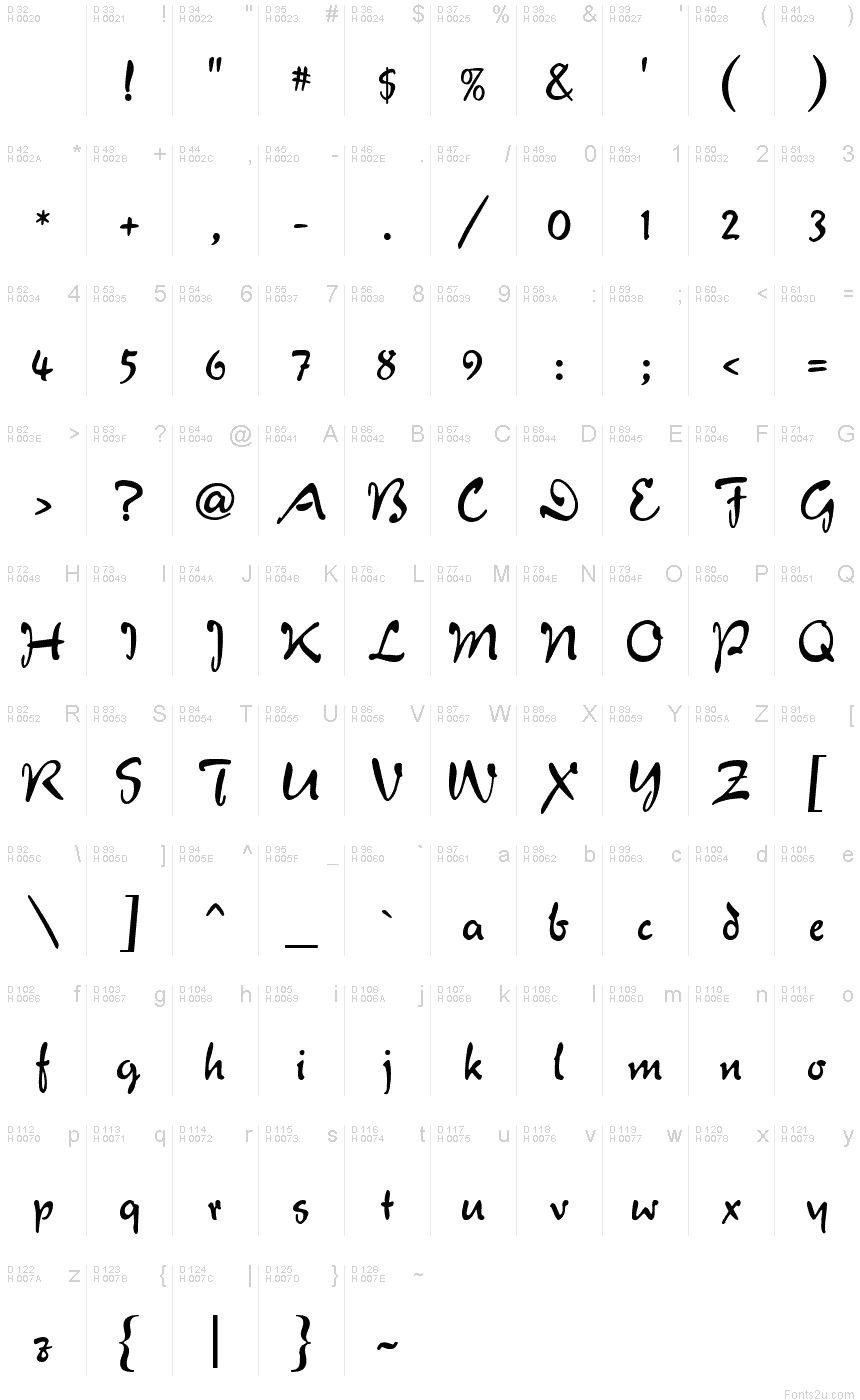
Verona Script
Verona Script autorstwa Richarda Williama Muellera to darmowy krój pisma typu brush script z żywym, malarskim charakterem. Litery łączą szerokie, atramentowe pociągnięcia z wąskimi łączeniami i zaokrąglonymi, kroplowatymi wykończeniami, dzięki czemu font sprawia wrażenie szybkiego, odręcznego i nieco teatralnego, a nie wygładzonego.
Idealnie sprawdzi się w nagłówkach plakatów, butikowym brandingu, na okładkach książek, w menu kawiarni czy na planszach tytułowych, gdzie darmowy font potrzebuje dynamiki i ludzkiego pierwiastka. Wykorzystaj go, gdy krótkie słowa lub imiona wymagają efektownego wstępu i kilku miękkich, zapętlonych kształtów, aby nadać klimat bez popadania w formalną kaligrafię.